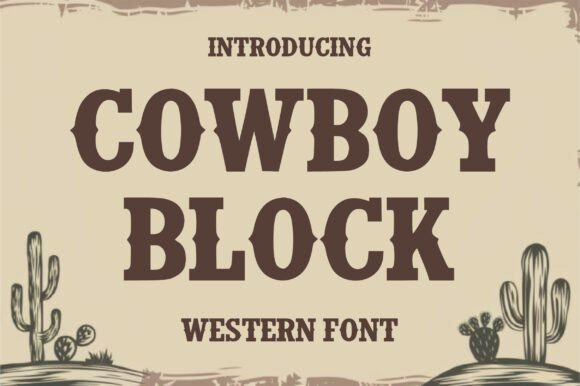
Cowboy Block
Việc tìm kiếm các thành phần thiết kế phù hợp có thể là một thách thức, nhưng Cowboy Block cung cấp một bộ sưu tập đặc biệt giúp nâng tầm công việc của bạn ngay lập tức.
Được chế tác với độ chính xác cao, Cowboy Block cung cấp các vector sạch, kiểu chữ mượt mà và giấy phép thương mại để bạn yên tâm.
Cho dù bạn đang tạo sản phẩm POD (In theo yêu cầu), thiệp mời đám cưới hay đồ họa mạng xã hội, Cowboy Block đều là một sự lựa chọn lý tưởng.